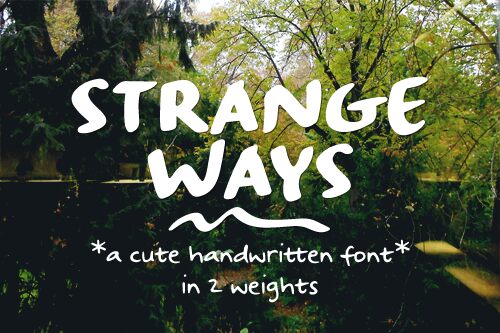
"Strangeways" ist eine charmante, handgeschriebene Schriftart, die Folgendes bietet:
- A-Z, a-z, 0-9, Akzente, Satzzeichen und Symbole
- Ligaturen
Strangeways Sample